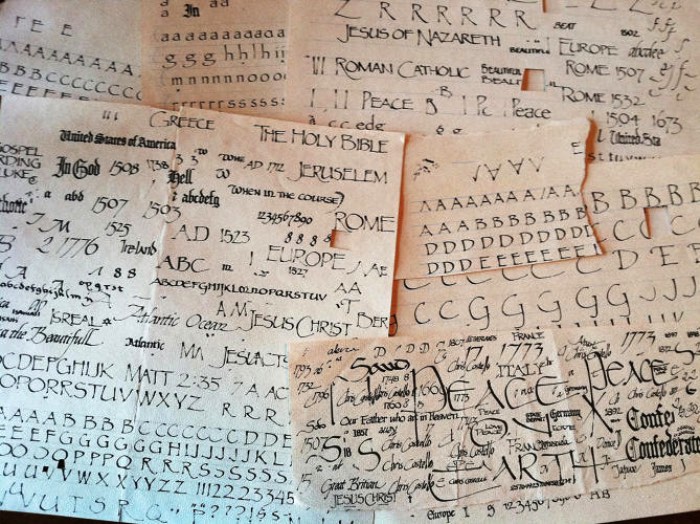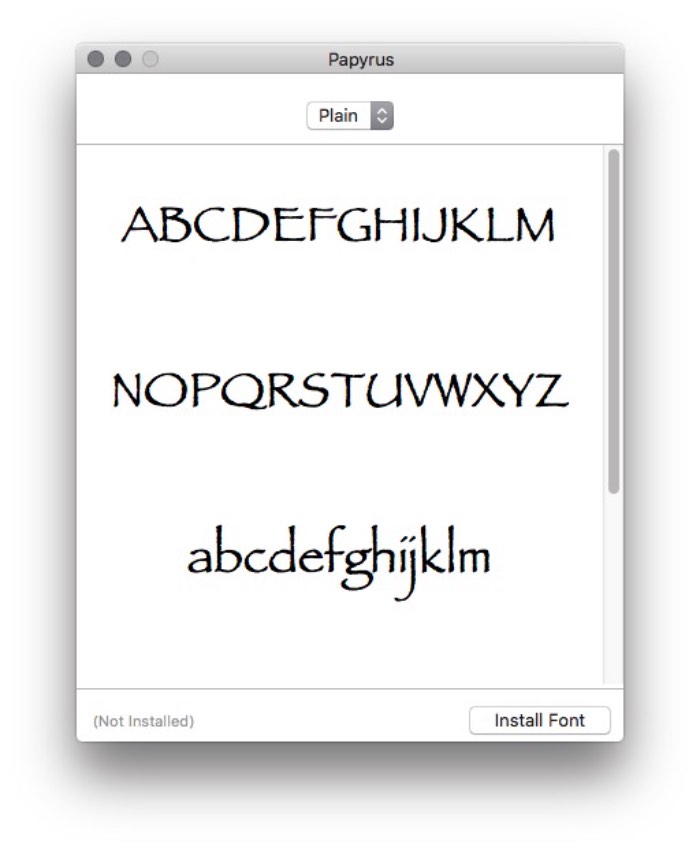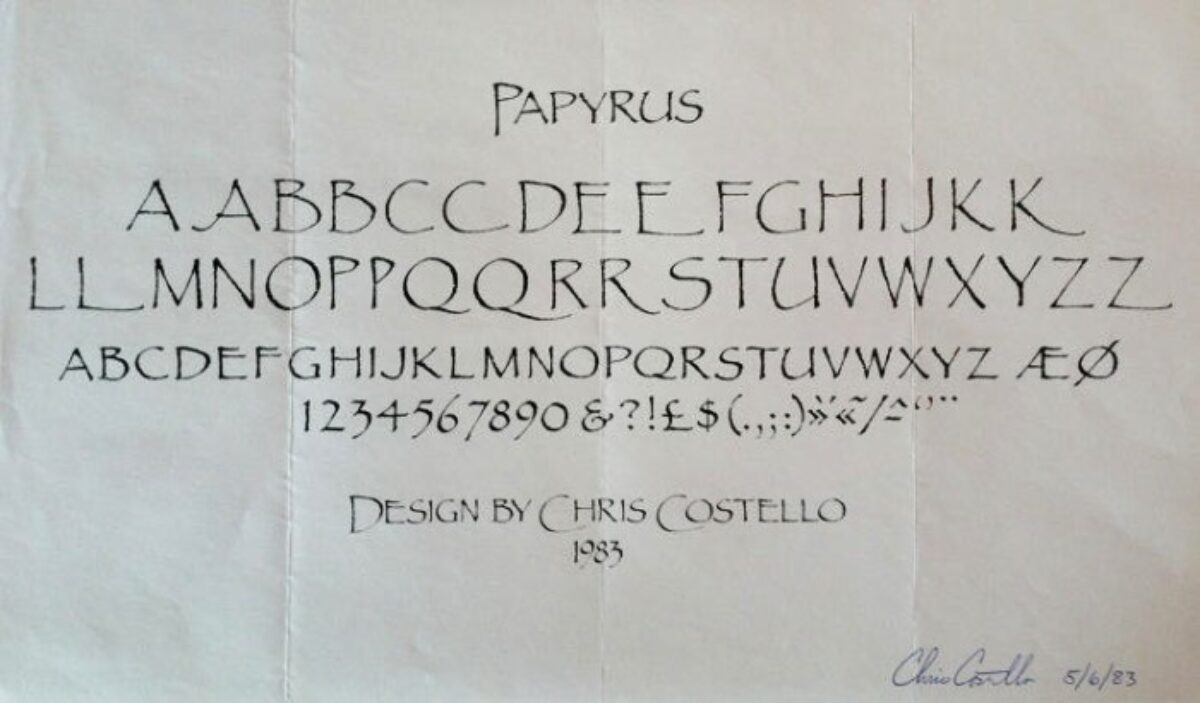
Já falei sobre a Comic Sans algumas vezes aqui mas não consegui descobrir se já falei sobre a fonte que eu mais odeio na história. Essa fonte é a Papyrus e, hoje, descobri que seu criador tem nome e ele se chama Chris Costello. Esse é o nome do responsável pela criação da Papyrus em 1982.
Para mim, Papyrus é uma das fontes mais desnecessárias já feitas. Seu visual é quase hilário, seus traços são forçados e seu uso errôneo deixa tudo ainda mais patético. Eu não gosto da Papyrus e vocês precisavam estar no cinema quando eu vi essa fonte surgindo, em tamanho gigantesco, durante o filme Avatar. Sei que não estou sozinho nesse ódio tipográfico e é por isso mesmo que estamos aqui escrevendo esse texto.
Um pouco da História de Chris Costello
Chris Costello nasceu en Nova Iorque na década de sessenta, seu pai era um pintor de placas e ele conheceu tipografia, lettering e computadores desde a infância. Seu pai é a ligação que ele tinha com esse mundo de letras e foi assim que ele começou nesse mundo. Quando ele saiu da escola, ele foi estudar no Instituto de Arte de Fort Lauderdale na Flórida, onde ele estudou publicidade e design. Quando saiu da universidade, ele foi contratado num agência de publicidade, aos 23 anos, e foi lá que a Papyrus nasceu. Alguns dizem que foi um nascimento acidental mas eu prefiro não acreditar nisso.
A Papyrus nasceu durante os períodos que Chris Costello passava sem trabalhos. Durante esse tempo livre, ele resolveu experimentar com tipografia e lettering, rascunhando ideias e conceitos. E, em 1983, lá estava ele desenhando letras quando ele começou a fazer pequenos traços em letras maiúsculas. Foi assim que ele percebeu que estava fazendo algo interessante. Sua cabeça apontou para o Oriente Médio, Deus e tempos bíblicos e Chris Costello passou a desenhar mais e mais letras com um visual de bordas distorcidas e traços horizontais fortes.
Ele viu algo interessante nos traços que estava fazendo e ele continuou, por alguns dias, desenhando todas as letras maiúsculas dessa que se tornaria a Papyrus. Depois de finalizar sua criação, Chris Costello resolveu ver se alguma distribuidora tipográfica teria interesse na sua fonte e ele só recebeu nãos. A Papyrus começou sua vida sendo rejeitada e eu não sei porque isso mudou.
Papyrus e Letraset
Foi ai que a Papyrus chegou a Letraset, uma pequena empresa britânica que parece ter sido a criadora do texto Lorem Ipsum. O pessoal da Letraset gostou da Papyrus e, depois de algumas pequenas alterações, acabaram comprando os direitos dessa fonte por cerca de 750 Libras. Algo como $2500 dólares, na época. Chris Costello tinha 23 anos e tinha acabado de vender os direitos da sua primeira fonte e esse dinheiro é um dos poucos motivos pelos quais ele acredita que ele cometeu um erro.
A Papyrus apareceu no catálogo da Letraset em 1984 e não foi um sucesso imediato. Por cerca de 15 anos, o mundo ignorou essa fonte e isso só mudou quando a fonte foi escolhida pela Microsoft para ser inserida no pacote do Office em 1997. Foi assim que o mundo foi apresentado a Papyrus e foi ai que eu descobri meu ódio por essa fonte.
Se você parar para fazer as contas, até 2012, pelo menos um bilhão de pessoas entraram em contato com essa fonte que eu odeio tanto. Isso apenas no lado do Windows mas, desde 2003, a Papyrus também existe no OS/X da Apple. Você pode colocar mais uns 100 milhões de usuários ai na conta. O que faz com que, pelo menos, uma em cada sete pessoas do planeta já viram essa fonte. Não sei se existe algo mais triste do que isso.
Hoje em dia, Chris Costello vive em Boston com sua família. Apesar da Papyrus ser seu trabalho mais conhecido, ele já criou trabalhos de qualidade. Ele trabalha com o serviço de Tesouro do Governo Americano e seu trabalho está nas moedas de dólar. Ele também já criou outras fontes que, mesmo não se tornando tão famosas, são bem melhores do que a Papyrus. E isso já me deixa um pouco mais aliviado.